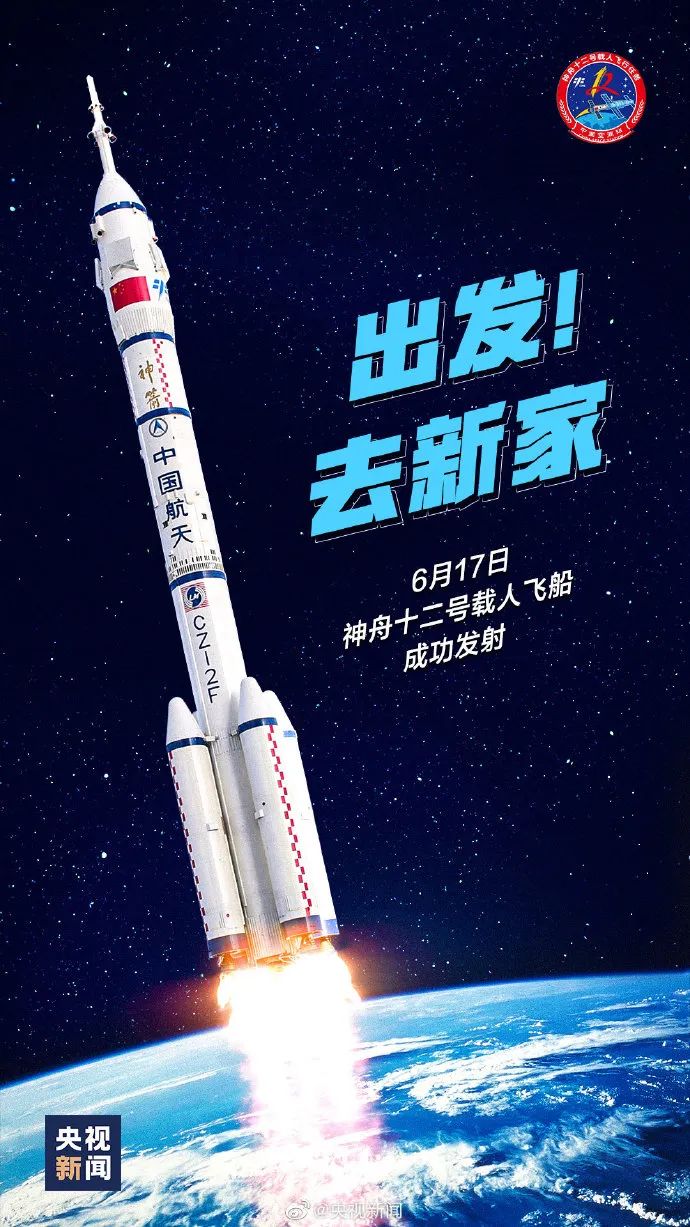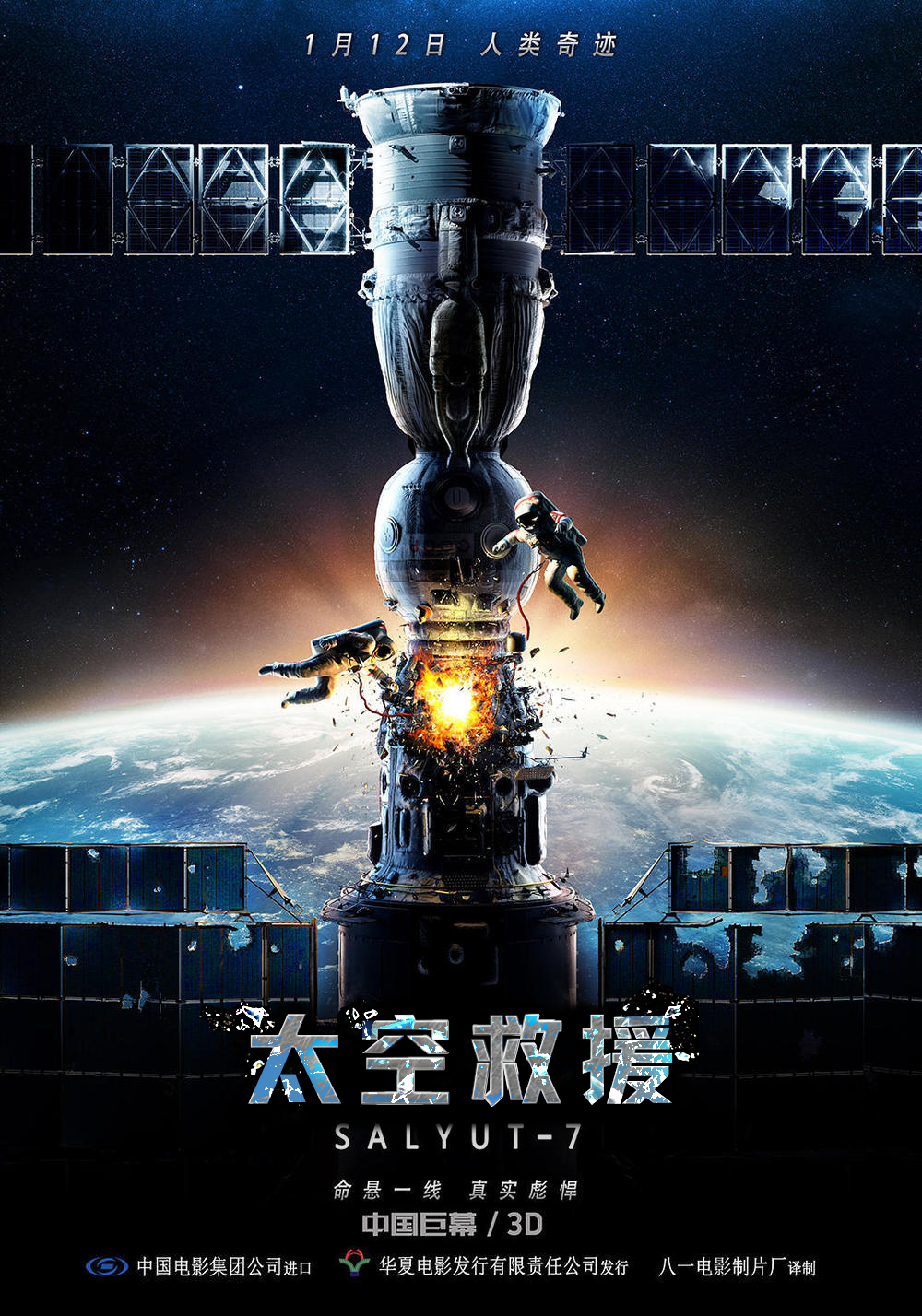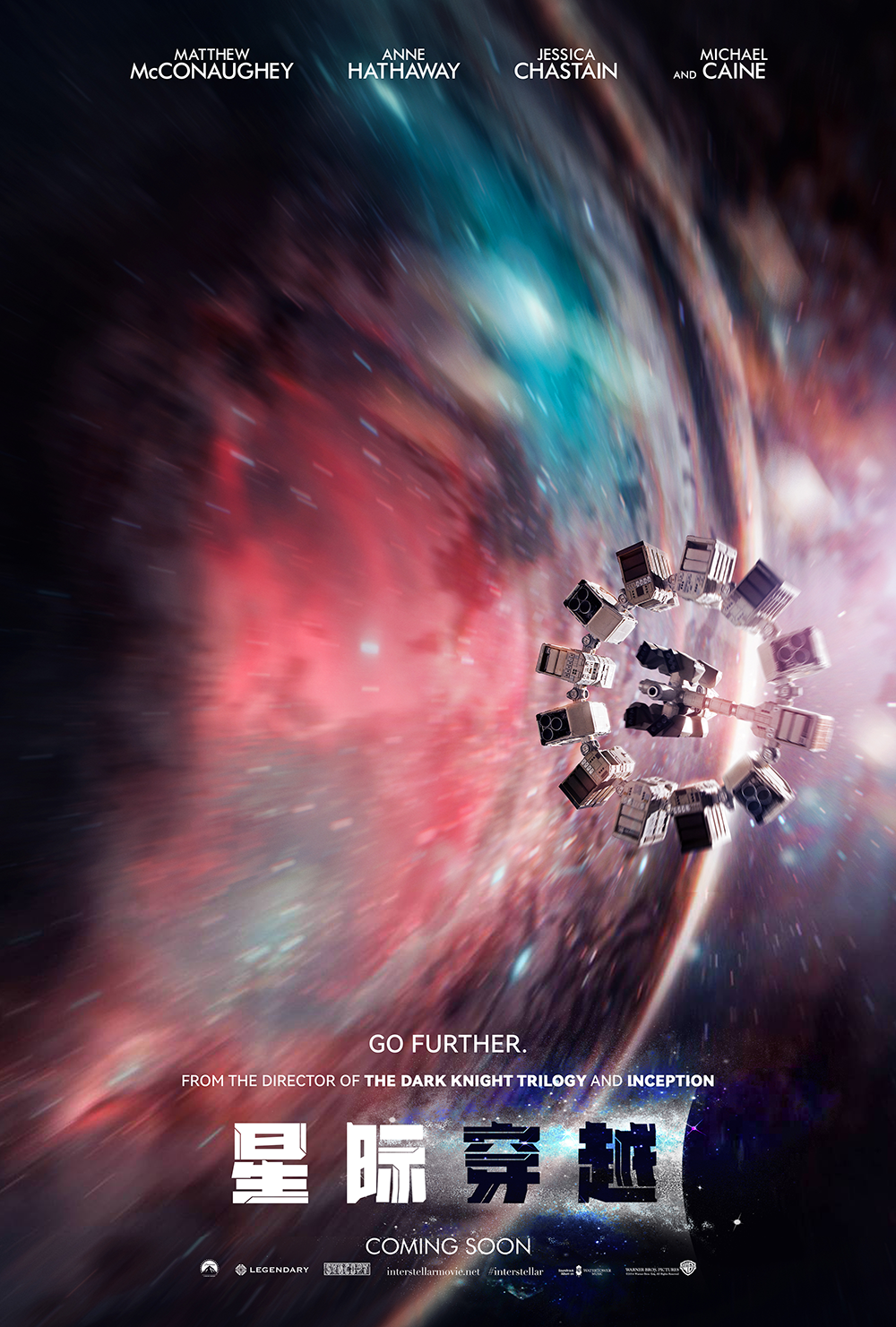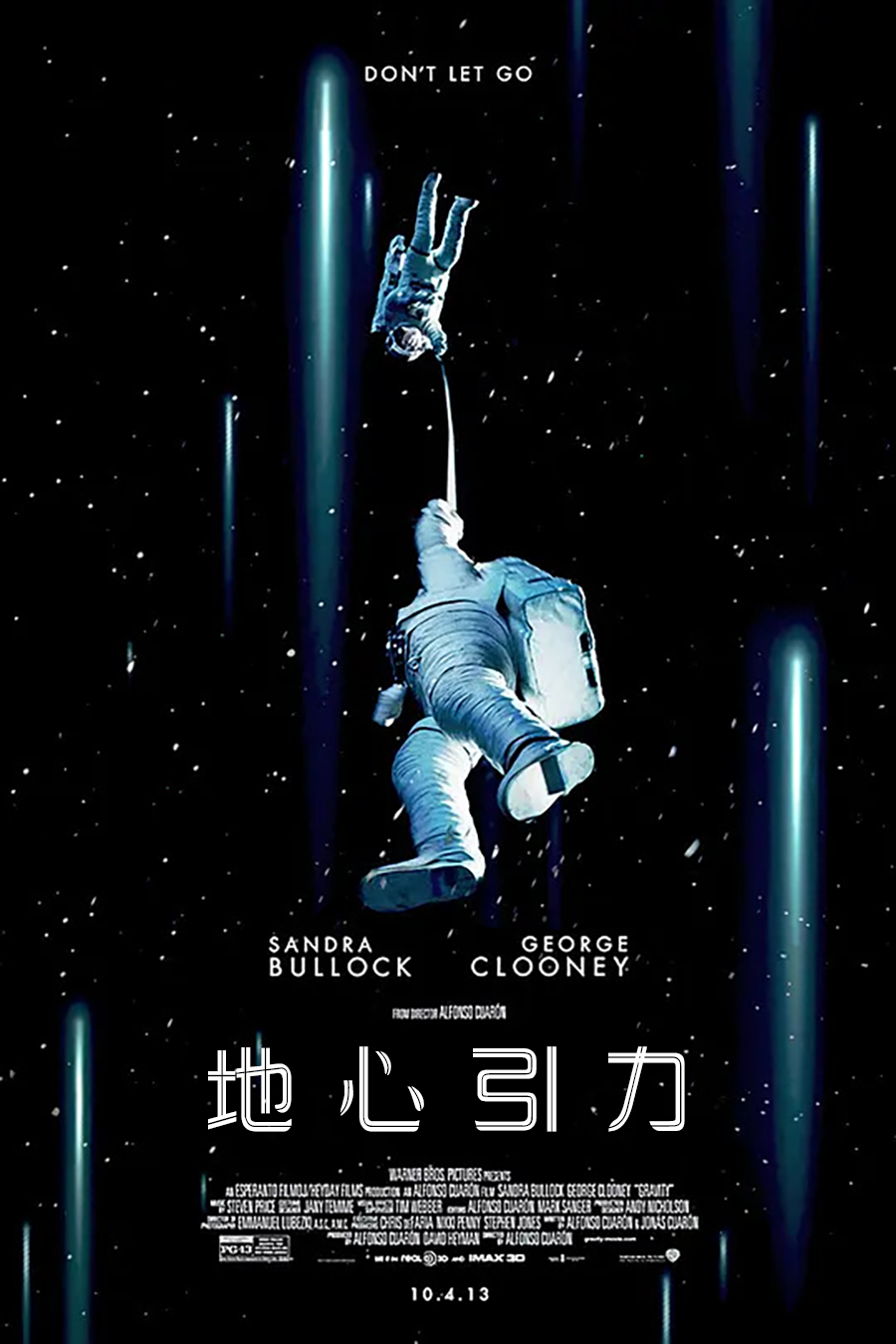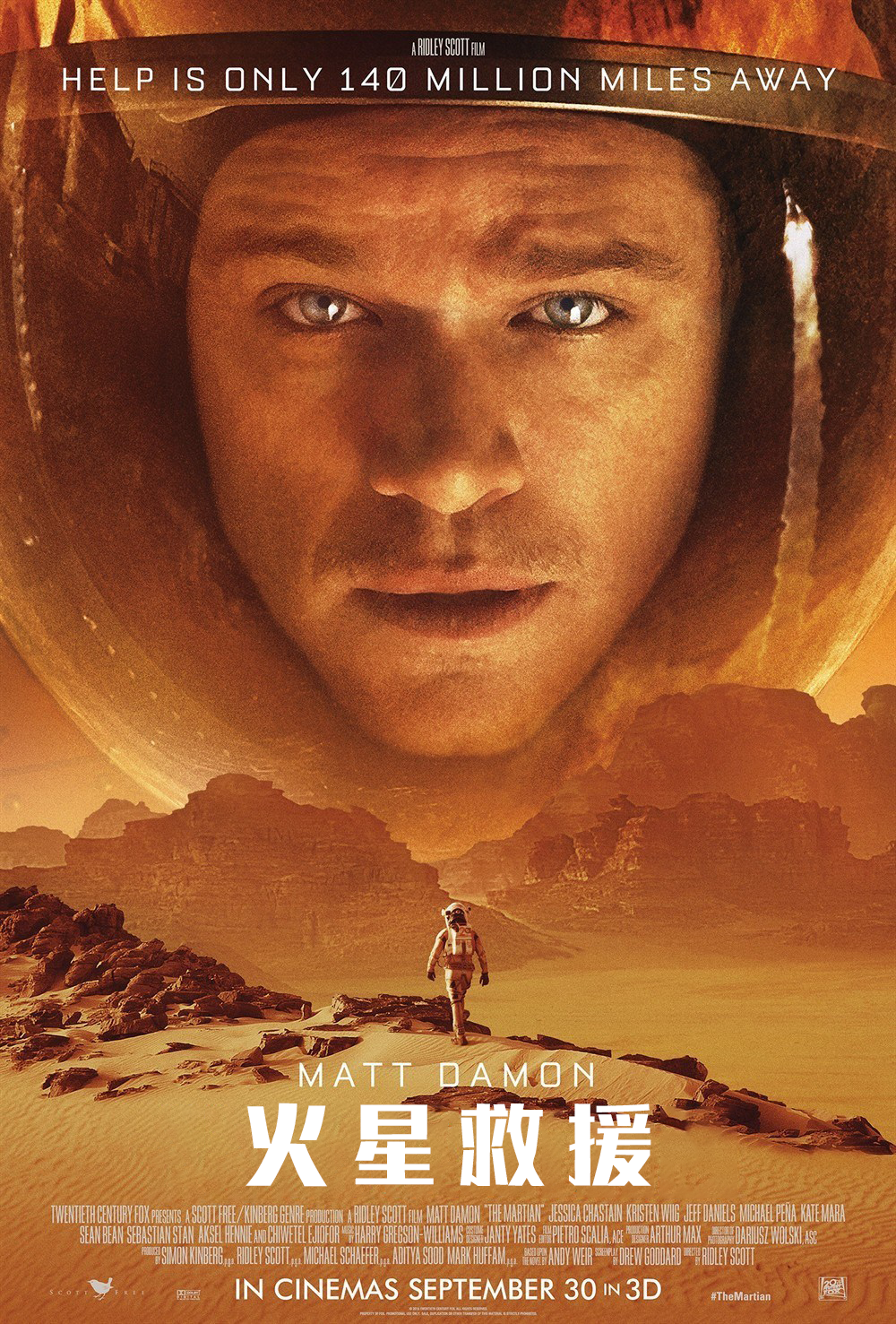
神舟十二,点燃了字体人的航天梦!
相信大家昨天都有在关注着神舟十二号的发射,虽然只有短短的十多分钟,但是柚子的心一直在提着,有担心有期待,但是更多的是骄傲🇨🇳🇨🇳🇨🇳直到看到央视新闻官方发布了发射成功的海报,才舒了一口气,定睛一看,这不是汉仪力量黑吗🚀下午4点左右,神舟十二号和天和核心舱的对接也是激动人心的时刻,直播的画面每一帧都是大片,自豪感upup↑😸在新技术“自主快速交汇对接”的加持下,安全系数和对接速度都得到了大大的提升,快到柚子根本就没!看!够!只能搜搜太空题材的电影过过瘾了😭柚子想到的第一部电影就是《太空救援》,由真实事件改编,返回舱和空间站的对接险象环生(神舟十二号就安全多了)。最经典的宇宙科幻电影非诺兰执导的《星际穿越》莫属,柚子起码刷了5遍,不看实在是大损失(星际穿越yyds)。上可遨游太空,下可代言高达,点字机械体就是科技的化身👍
还有奥斯卡最佳影片《地心引力》,讲的是在宇宙中求生的故事,也很值得一看!
《火星救援》应该都看过吧?堪称火星版的荒野求生。
利用高科技求生,坚定、顽强、聪明,和阿里汉仪智能黑体太配了!字体人也有航天梦,用字体为祖国的航空航天事业助力!望英雄们平安归来🇨🇳🇨🇳